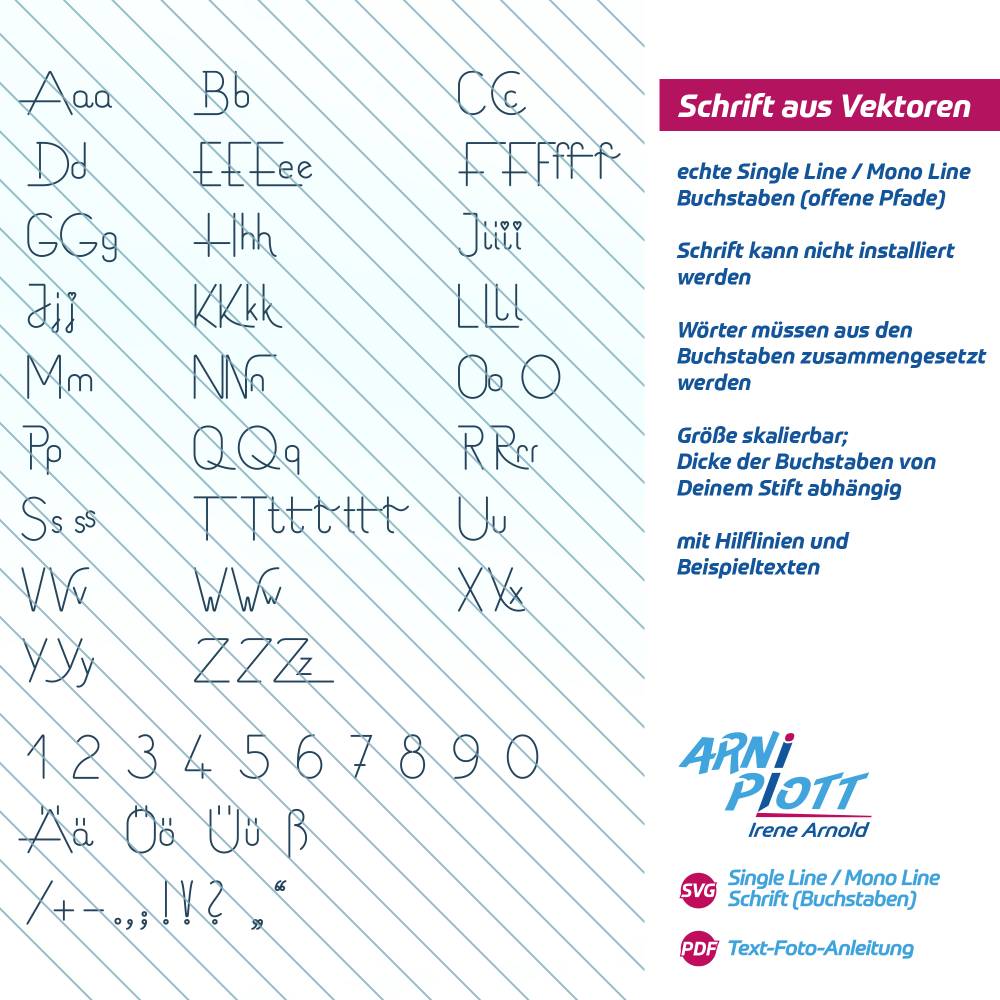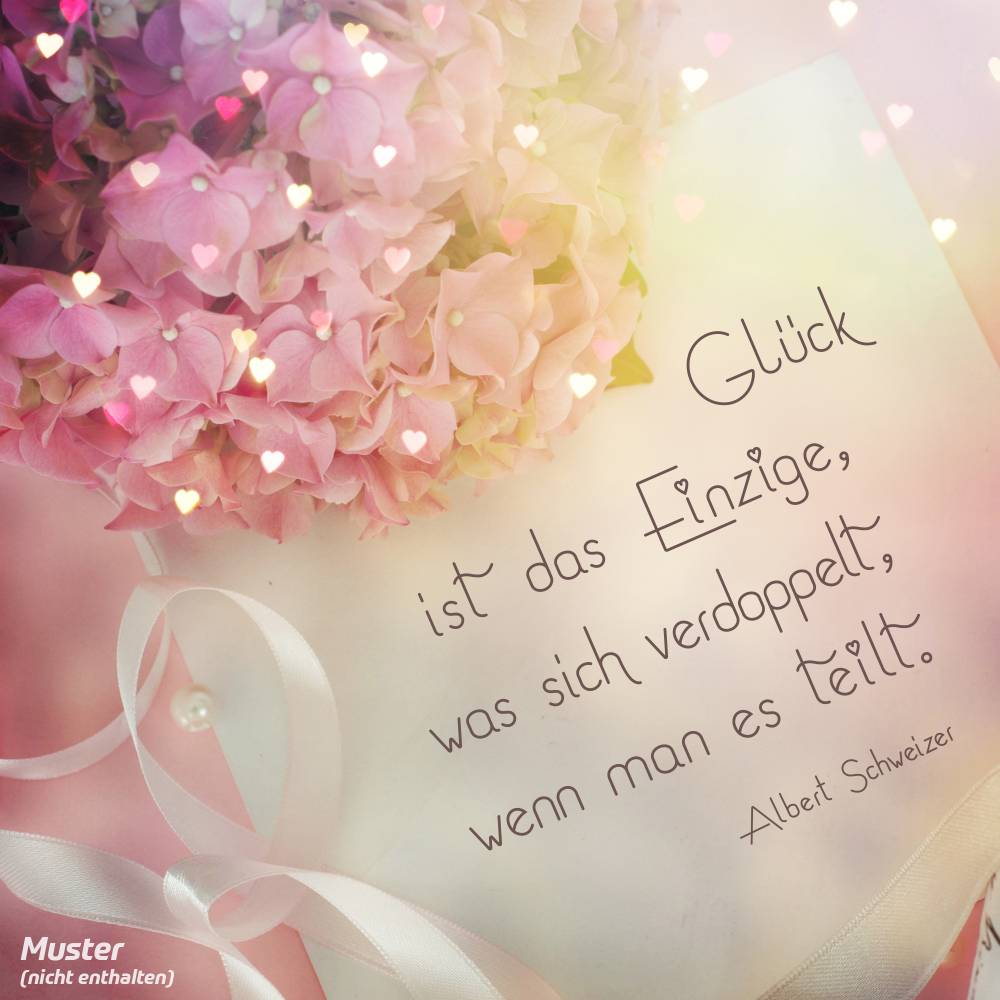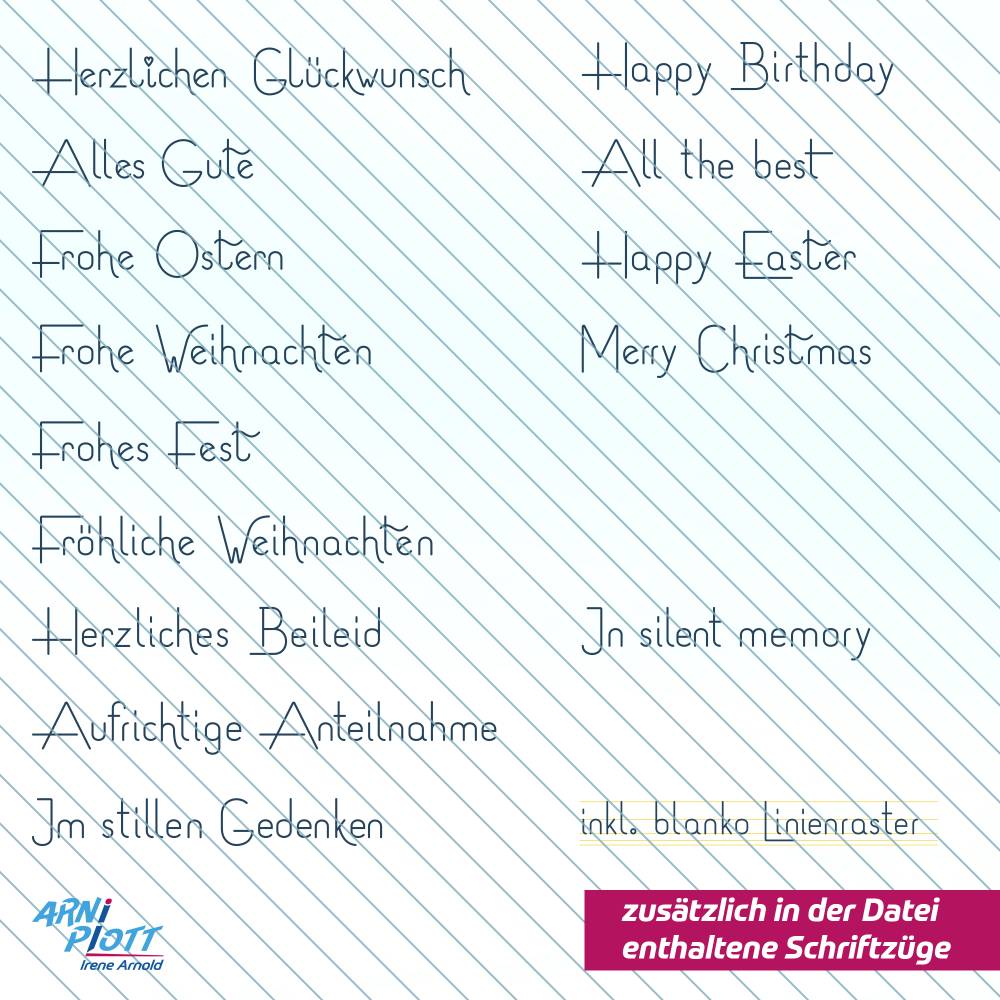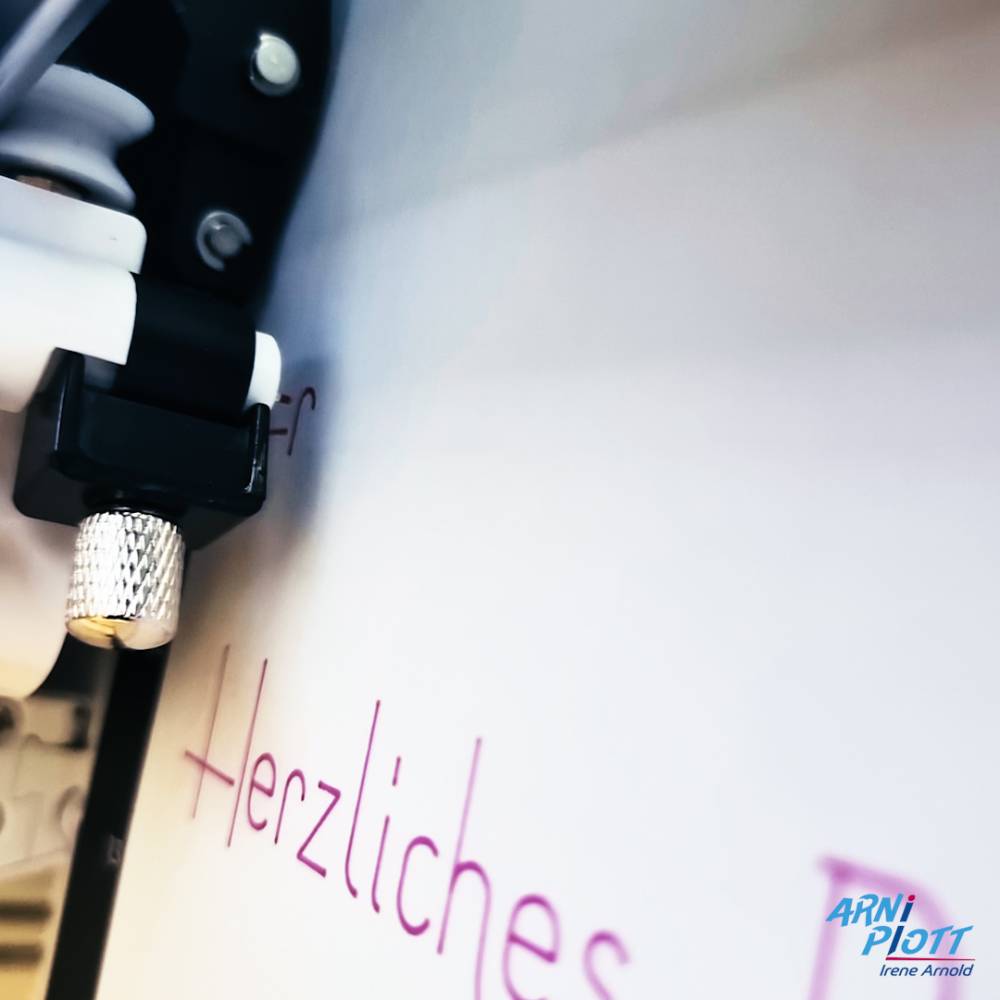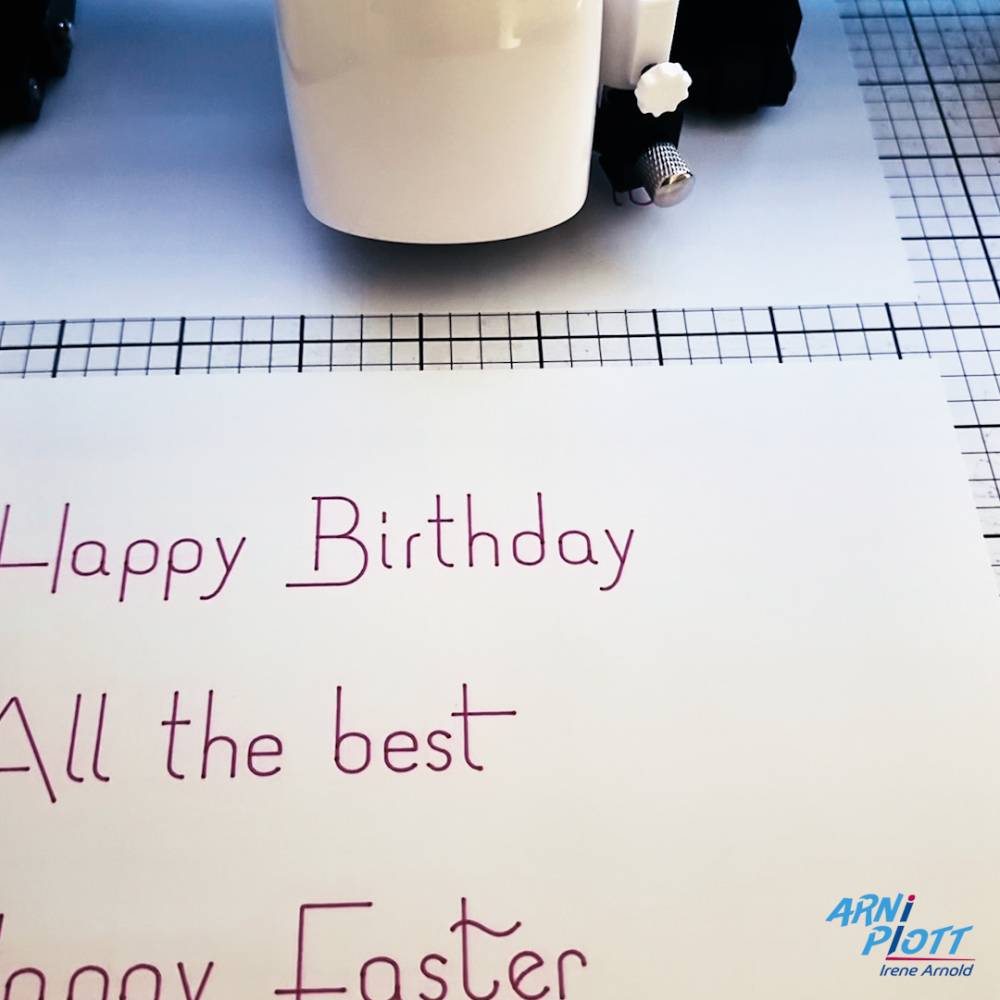
SVG echte Monoline Schrift, Singleline Font, Typografie Vektorformat, Zusammensetzen + Schreiben mit dem Plotter (Stift)
Wunderst und ärgerst Du Dich auch immer wieder, warum Dein Stift im Plotter die Schrift doppelt abfährt und häufig ein Leerraum innerhalb der Buchstaben entsteht? Mit dieser von mir konstruierten echten Singleline Schrift bzw. Monoline Font im SVG Vektorformat fährt der Stift Deines Plotters nur eine Linie ab und so  entsteht kein Leerraum – es ist kein Ausmalen und keine Fülldatei erforderlich. So wird Dir das Schreiben mit dem Plotter Freude bereiten und Deine Projektewerden noch bezaubernder aussehen und enorm aufgewertet.
Ein optionales Linienraster zum Zusammensetzen der Buchstaben zu Wörtern sowie14 bereits zusammengesetzte Kartengrüße sind in der Datei ebenfalls enthalten sowie selbstverständlich auch eine Anleitung.
Zugegeben, einen Nachteil hat diese Art von Schrift: Sie lässt sich aus technischen Gründen nicht im Computersystem wie eine normale Schrift installieren. Was zur Folge hat, dass Du Deinen Text nicht einfach tippen kannst, sondern die Buchstaben einzeln aneinanderreihen musst. Weitere Infos hierzu findest Du in der Anleitung.
Aber diese Art zu Schreiben hat auch einen enormen Vorteil: Du bist viel flexibler in der Gestaltung!
Zum Beispiel habe ich für einige Buchstaben unterschiedliche Variantenangelegt. So kannst Du während des Gestaltens entscheiden, ob Du eine eher cleane oder verspieltere Form des Buchstabens verwenden möchtest.
Vielleicht möchtest Du auch einmal einen Buchstaben aus der Reihe tanzen lassen– etwas höher oder größer setzen?
Fühl Dich frei und „spiele“ gern mit den Buchstaben! So gestaltest Du wundervolle und einmalige Texte für Deine Plotterprojekte!
Und natürlich kannst Du die Buchstabenbeliebig skalieren. Beachte dabei bitte, dass die Schriftstärke (die Dicke der einzelnen Linien) von Deinem Stift im Plotter abhängig ist. Eine dickere Stiftspitze zieht dickere Linien – und dies wiederum erfordert eher größere Buchstaben, die etwas weiter auseinander stehen sollten. Weitere Infos hierzu findest Du auch in der Anleitung.